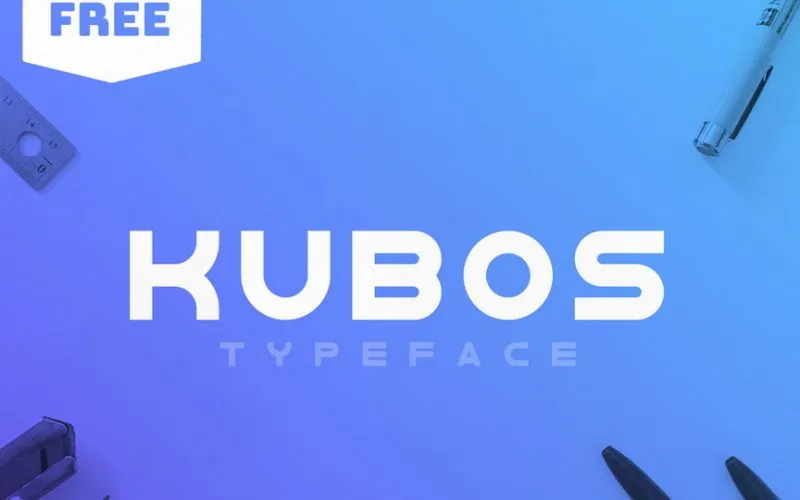
A fonte Kubos Typeface é uma opção perfeita para designers que buscam algo moderno e geométrico para seus projetos. Inspirada na palavra grega κύβος, que significa “caixa” ou “cubo”, essa fonte sans-serif apresenta um design simples à primeira vista, mas que revela um vasto potencial ao explorar o desafio de respeitar uma grade geométrica. Através da sua elegância e simplicidade, a Kubos Typeface oferece uma solução ideal para vários tipos de projetos, desde identidades visuais para marcas, embalagens de produtos, cabeçalhos de revistas até mesmo como um overlay de texto para qualquer imagem de fundo. Suas linhas retas e formas geométricas o tornam perfeito para quem busca uma fonte que se destaca, sem deixar de respeitar a importância de estruturas rígidas. Com seu design limpo e moderno, a Kubos Typeface é mais do que apenas um recurso gráfico; ela inspira criatividade e permite ao designer explorar suas próprias ideias. Para designers co-workers e amigos, o lançamento da fonte Kubos Font Free oferece uma ferramenta inestimável para tornar seus projetos ainda mais atraentes e inovadores.